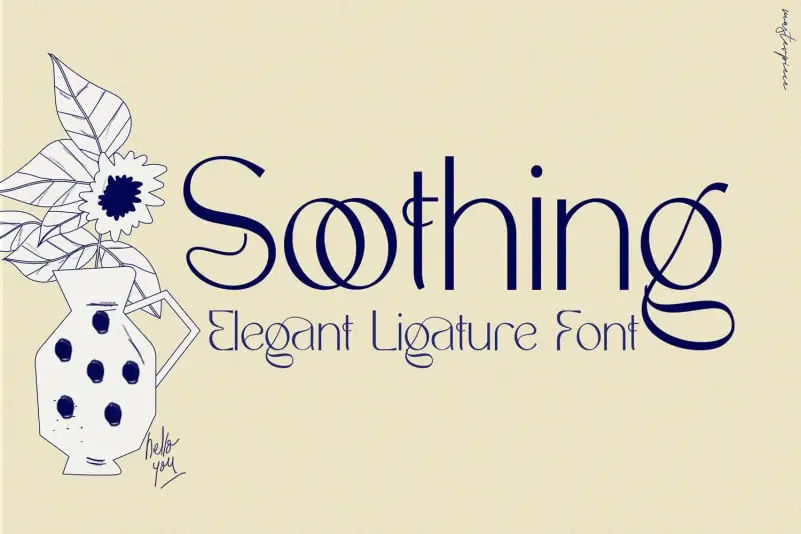
Soothing – Unique Ligature Font
A fonte ‘Soothing – Unique Ligature Font’ é uma escolha excepcional para design de logomarca e branding graças às suas características únicas e modernas, criadas por 177Studio. Ela é uma tipografia sans-serif elegante que usa ligaturas para unir letras com suavidade e sofisticação. Perfeita para estilos mais arredondados, a fonte ‘Soothing’ permite criar logomarcas e logos de alto padrão, que são tanto originais quanto clássicos. Seja em uma empresa moderna ou um projeto tradicional que busca um toque diferenciado, essa fonte lhe dará o resultado desejável. Ideal para designers gráficos procurando por algo novo e autêntico, ‘Soothing’ é definitivamente a escolha certa para trazer um brilho especial aos seus trabalhos de design de logo.